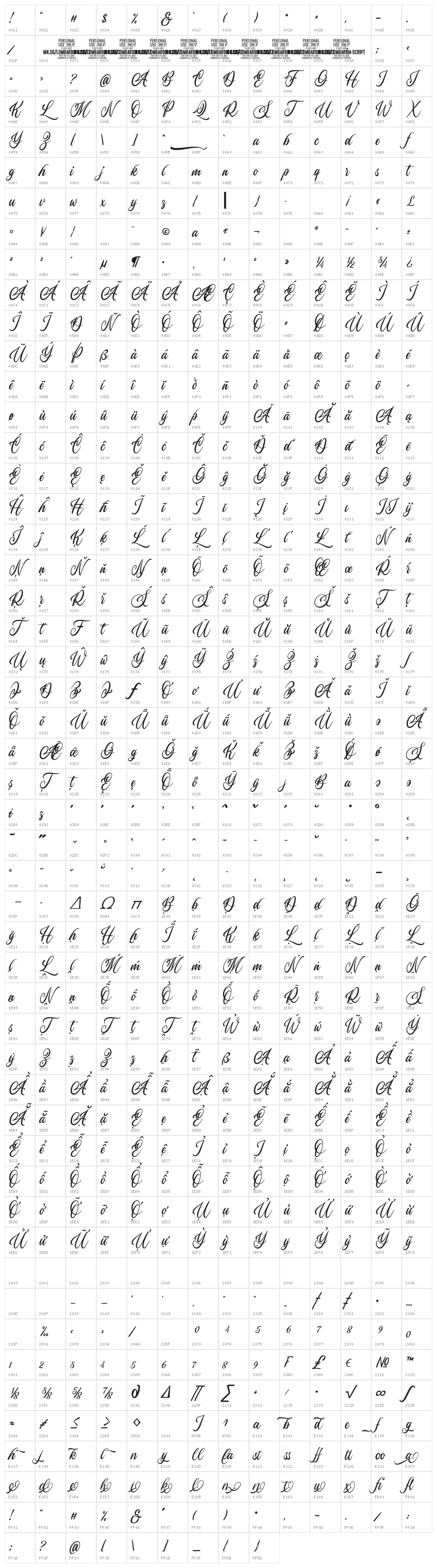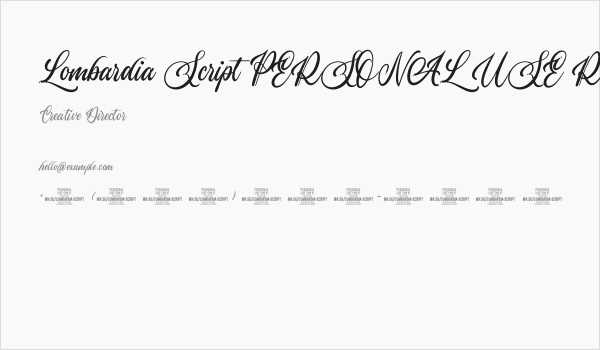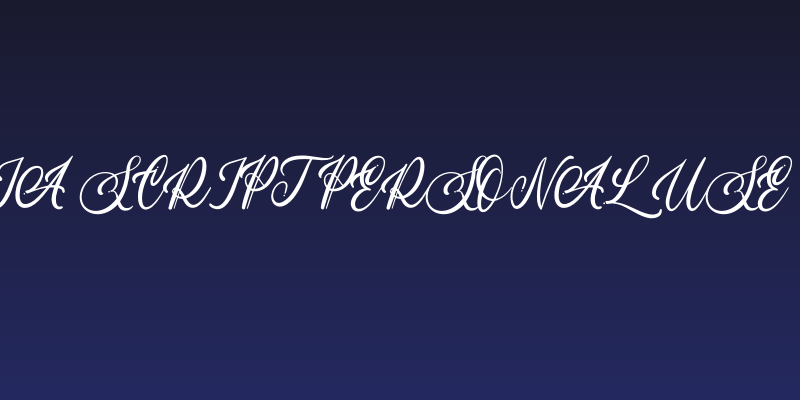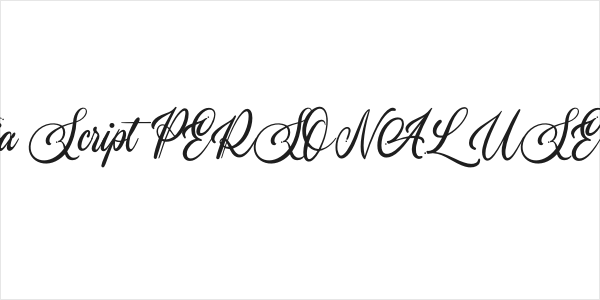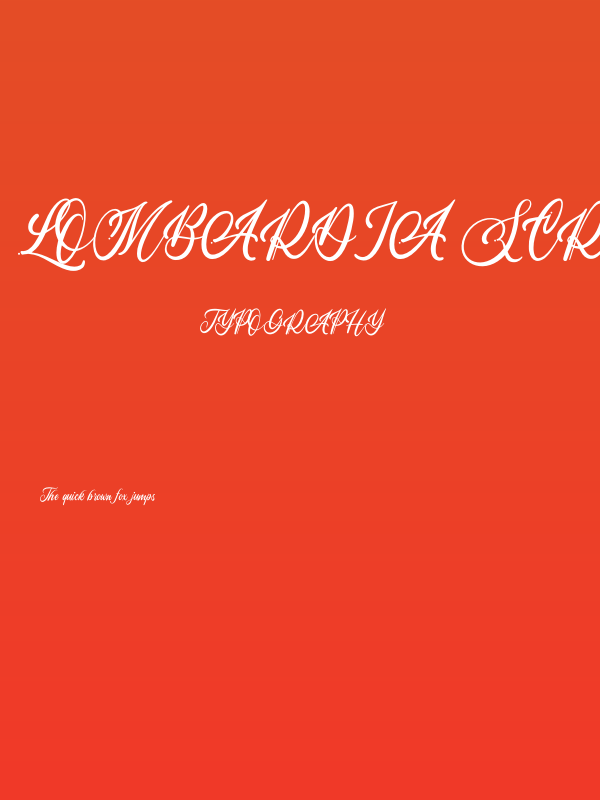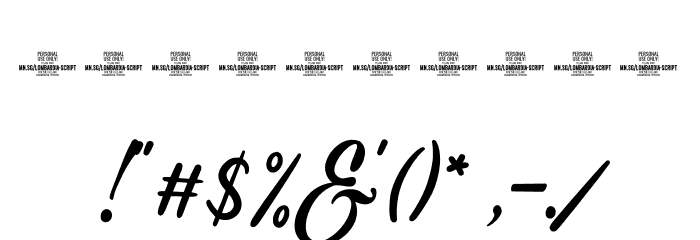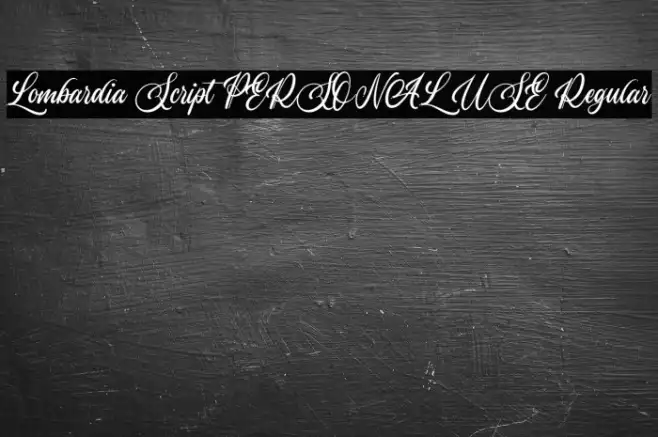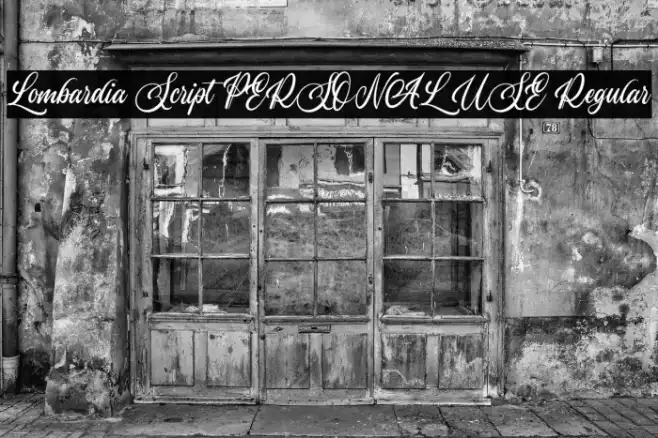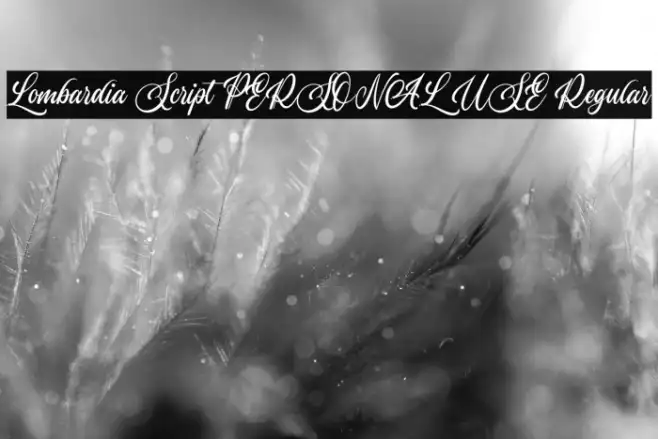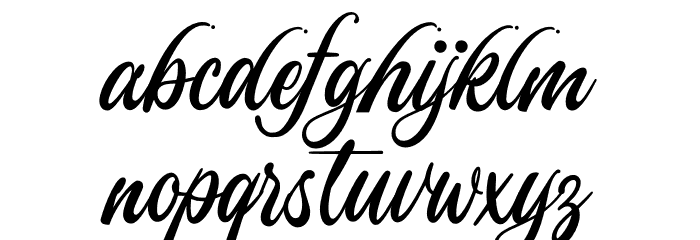
Lombardia Script PERSONAL USE Regular Font
| Name | Lombardia Script PERSONAL USE Regular |
| Schriften Familie | Lombardia Script PERSONAL USE |
| Kategorien | Script |
| Gesamtstil | Elegant, Decorative |
| Anwendungsfall | Logos, Invitations, Branding |
| Vorgeschlagene Projekte | Ideal for wedding invitations, luxury branding, elegant packaging, and high-end product labels. |